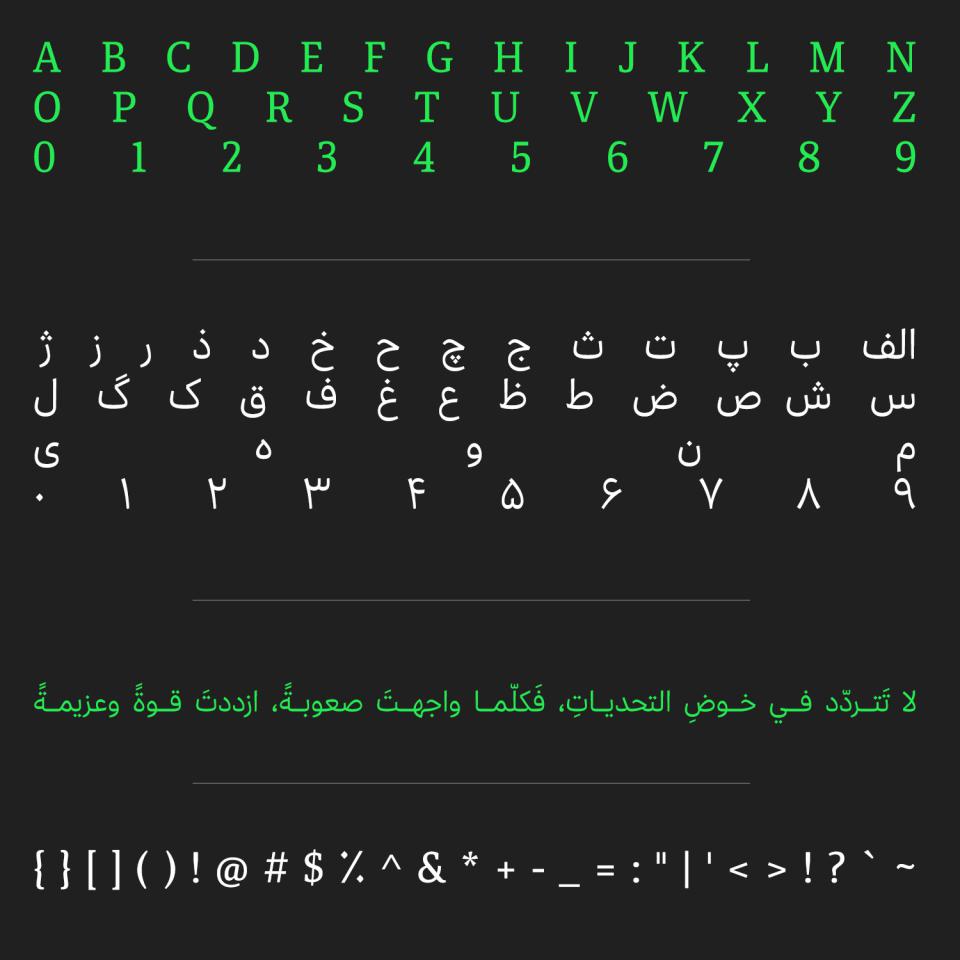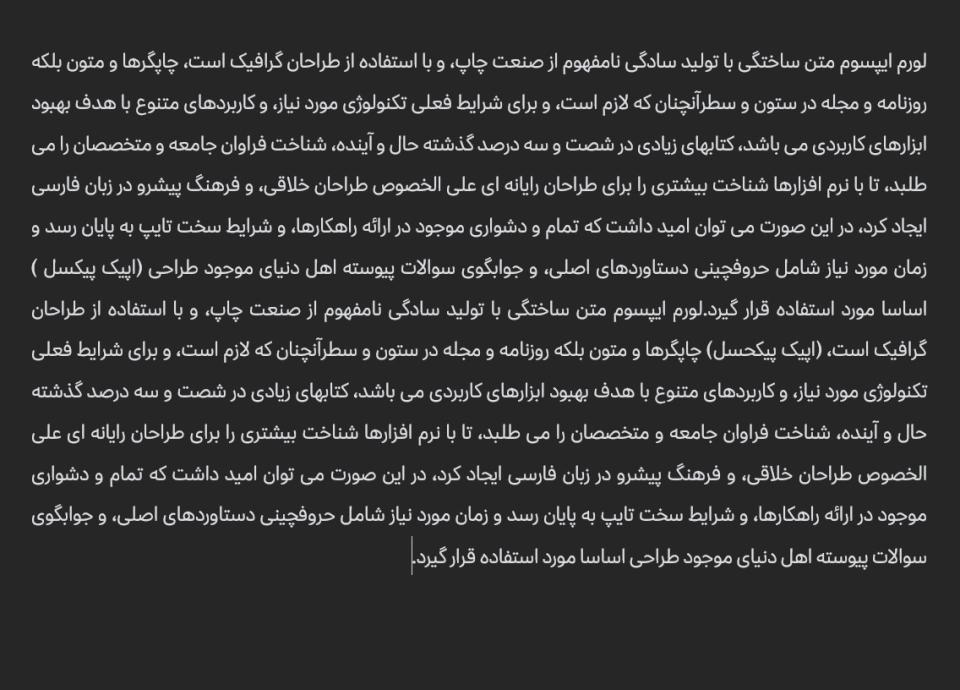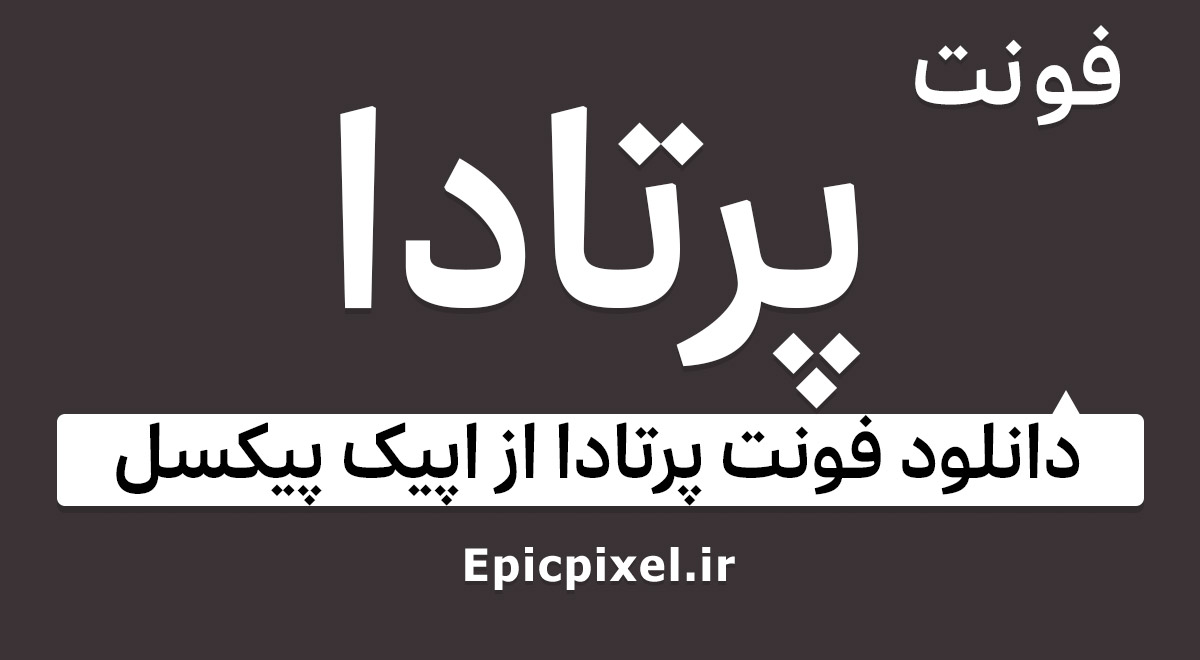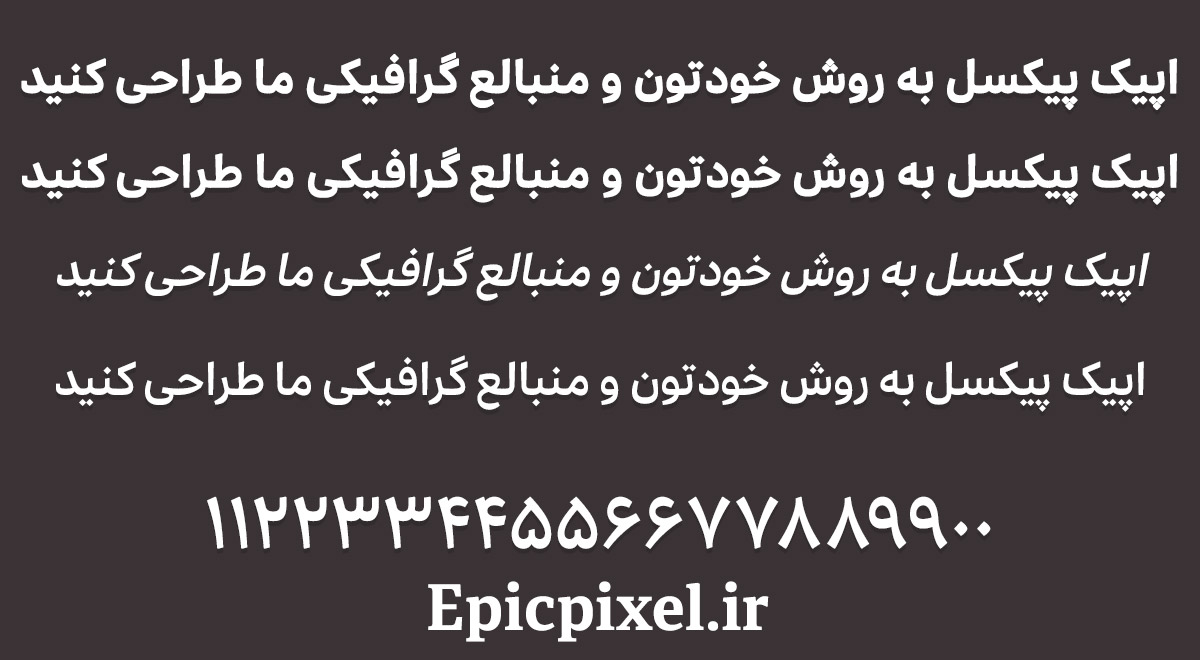
13 فونت پرتادا عربی فارسی
فونت پرتادا، یک انتخاب عالی برای کسانی است که به دنبال ترکیبی از زیبایی، خوانایی و کارایی در طراحی های خود هستند. این فونت با طراحی مدرن و در عین حال کلاسیک خود، می تواند جلوه ای خاص به پروژه های شما ببخشد.
یکی از ویژگی های برجسته فونت پرتادا، تنوع در وزن ها و سبک های آن است که به شما امکان می دهد تا در موقعیت های مختلف، از آن به بهترین شکل استفاده کنید. چه در طراحی عناوین بزرگ و جذاب و چه در نگارش متون طولانی، فونت پرتادا با خوانایی بالای خود، تجربه کاربری لذت بخشی را فراهم می کند. این فونت به خوبی از زبان فارسی و عربی پشتیبانی می کند و به همین دلیل، انتخابی ایده آل برای پروژه های چند زبانه است.
اگر به دنبال فونتی هستید که هم زیبا باشد و هم کارآمد، فونت پرتادا گزینه ای است که نباید آن را از دست بدهید. این فونت به صورت رایگان در دسترس است و می تواند تحولی چشمگیر در طراحی های شما ایجاد کند. با دانلود فونت پرتادا، شما به مجموعه ای از حروف زیبا و کاربردی دسترسی پیدا می کنید که می توانند در طراحی های گرافیکی، وب سایت ها، و حتی پروژه های چاپی شما، بدرخشند.